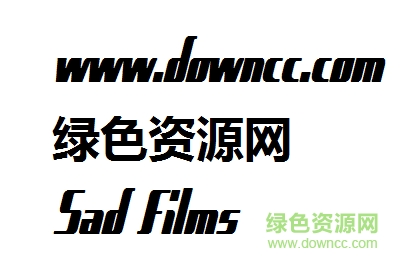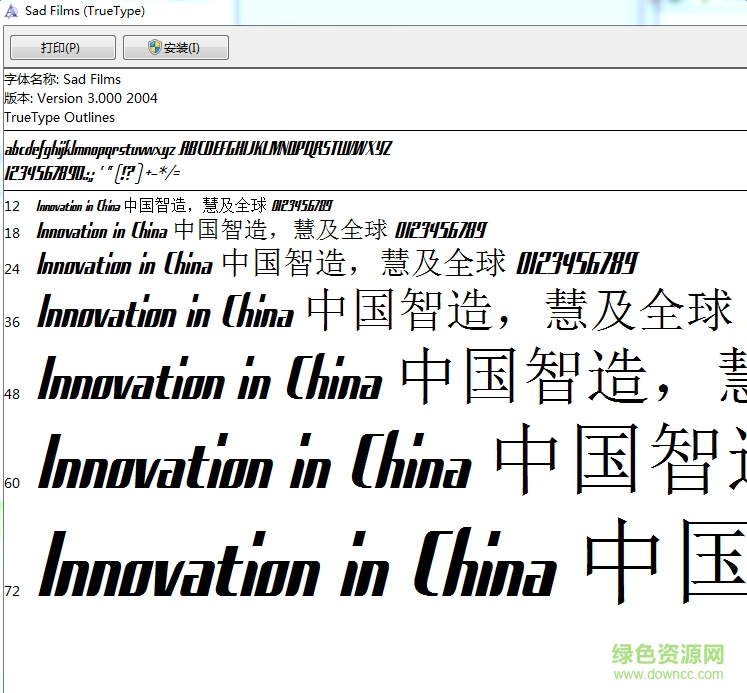
Sad Films字體是英文字體系列中經(jīng)典的一款時(shí)尚優(yōu)雅字體,線條變化自然,Sad Films字形創(chuàng)意十足,整體雅致美觀,可應(yīng)用于時(shí)尚雜志或宣傳海報(bào)等領(lǐng)域,綠色資源網(wǎng)還有更多免費(fèi)字體下載哦!
Sad Films字體是一款深受設(shè)計(jì)師喜愛的字體,此款字體具有一定的藝術(shù)感,易讀性非常強(qiáng),字體相對(duì)來說比較完整,應(yīng)用范圍比較廣泛,喜歡的朋友歡迎來綠色資源網(wǎng)下載收藏!